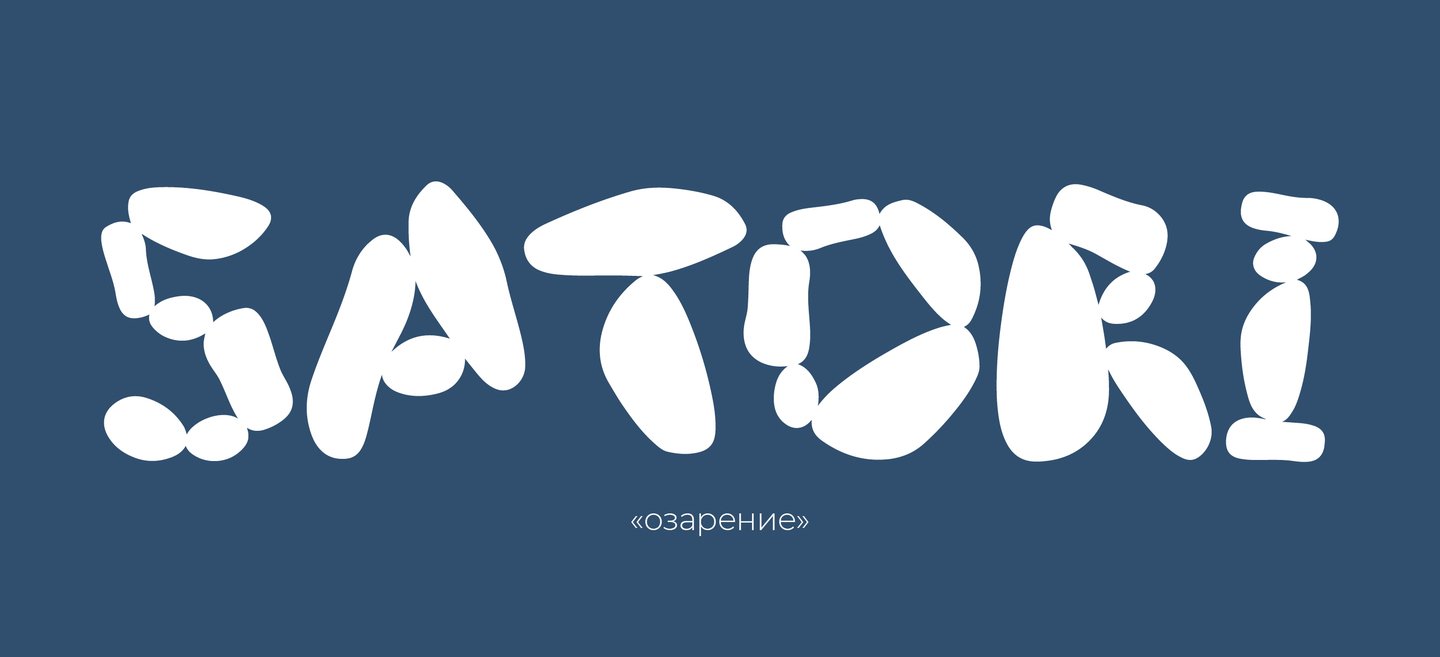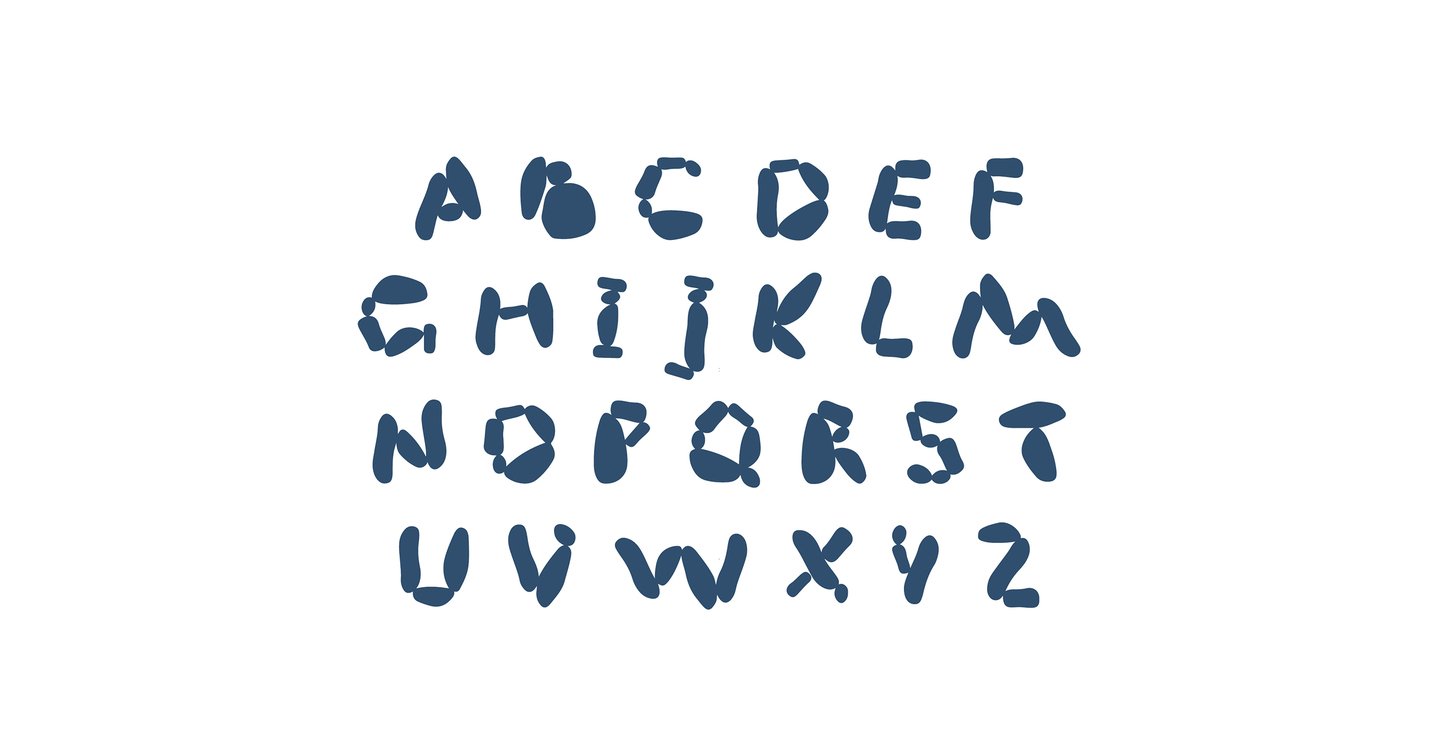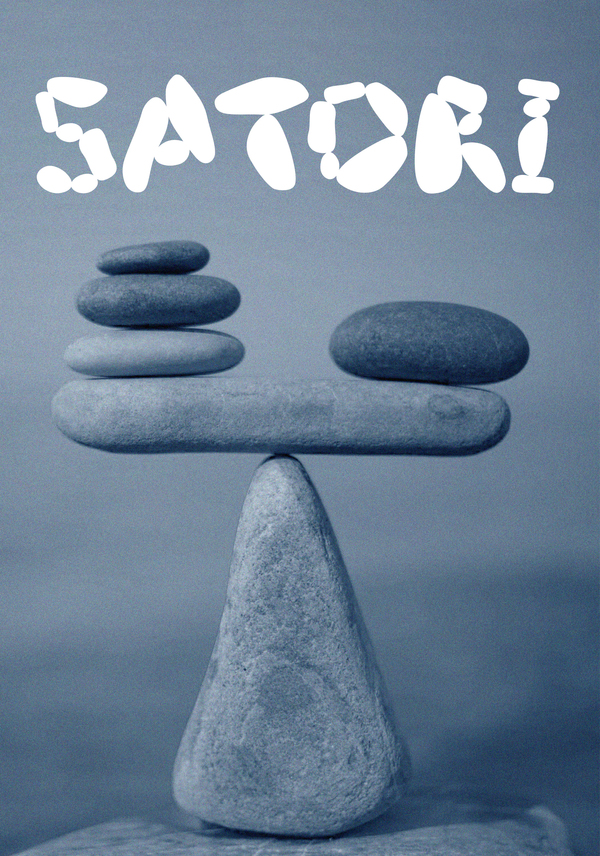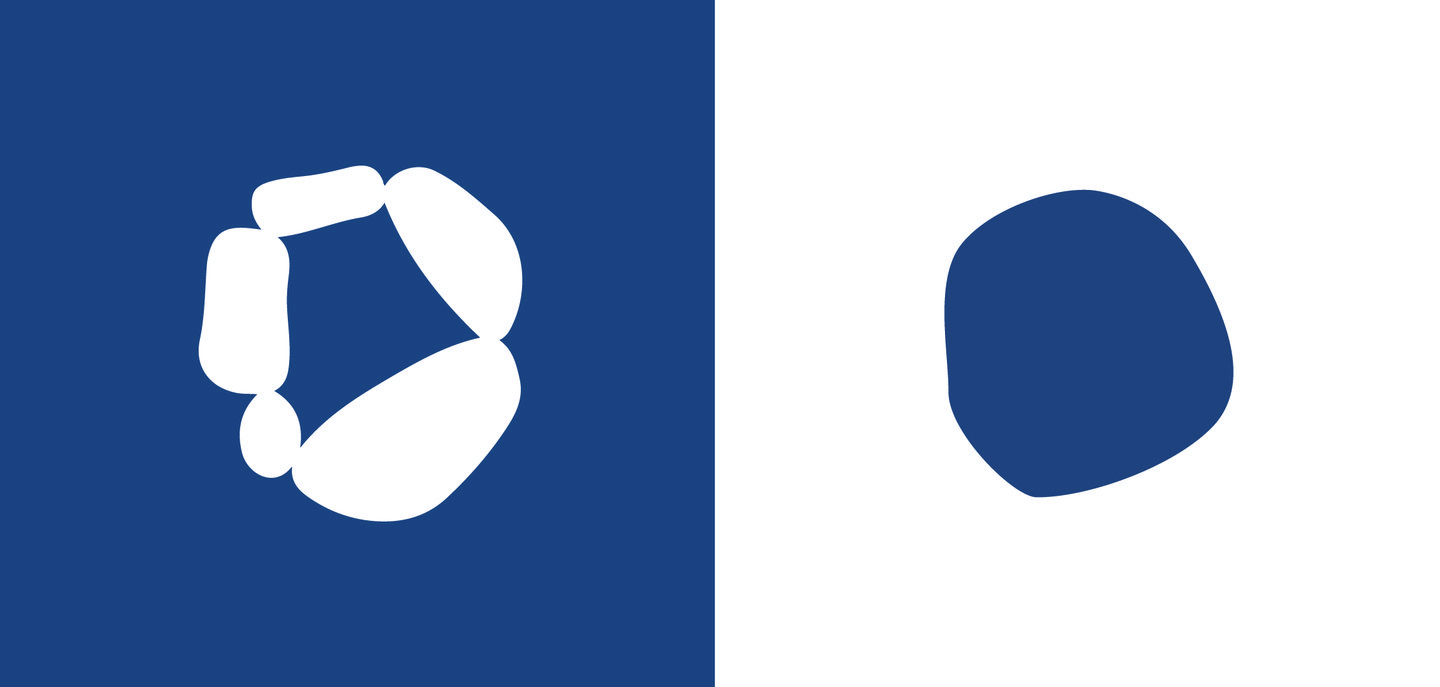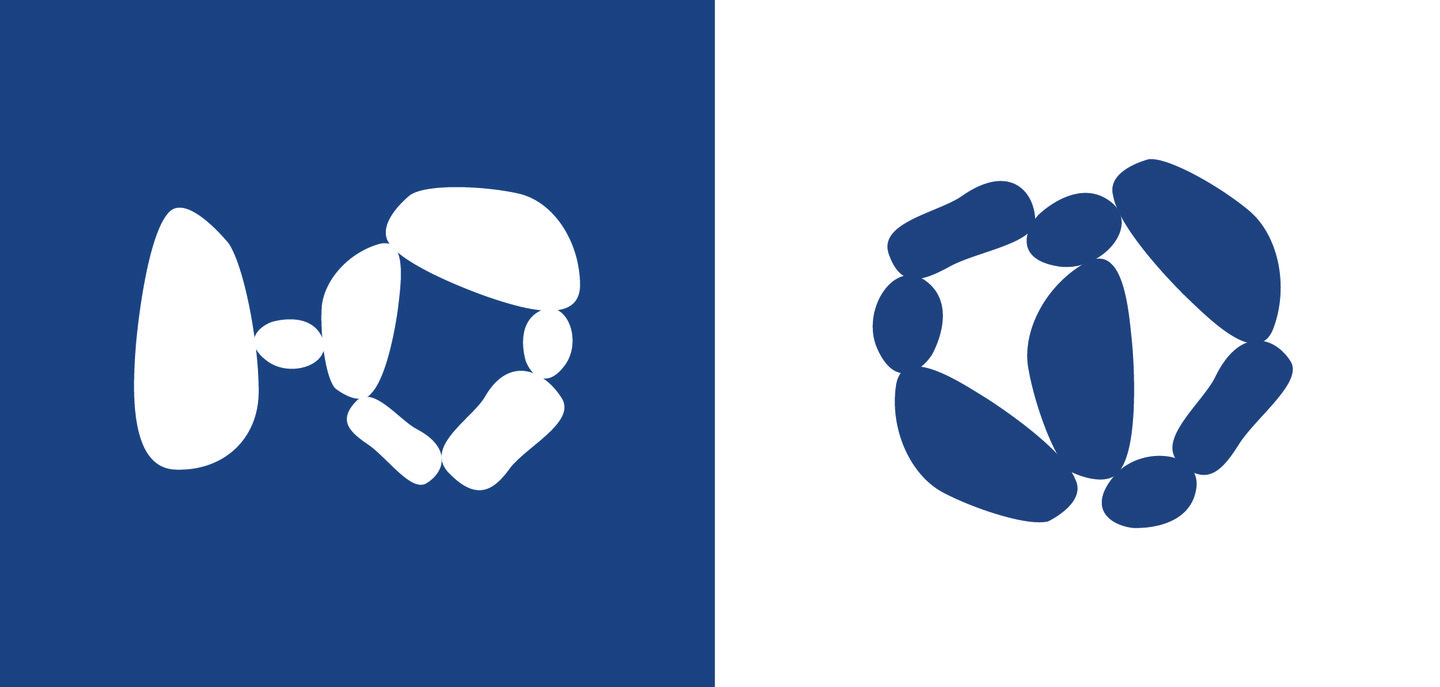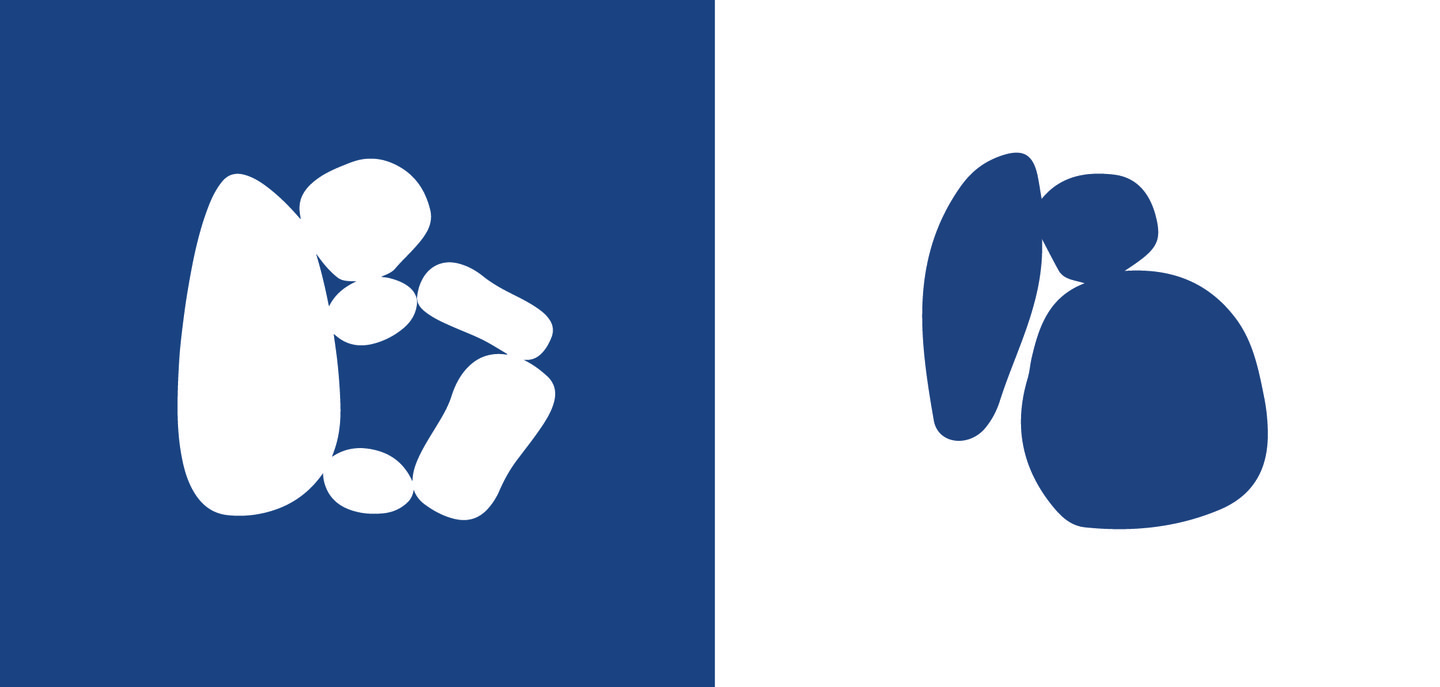
Satori Font — модульный шрифт, созданный на основе форм камней, найденных на берегу моря. Исследование началось с наблюдения за природными силуэтами и поиска визуально интересных форм. Выделенные очертания камней были упрощены и использованы как модули для построения букв.
(латиница)
(кириллица)
(символы)